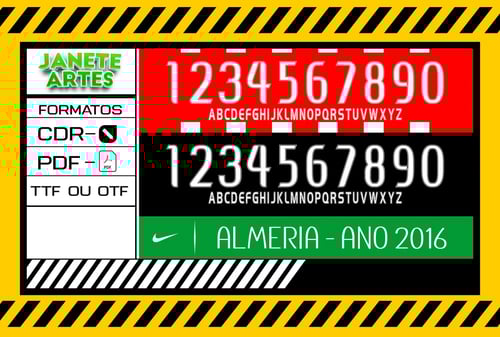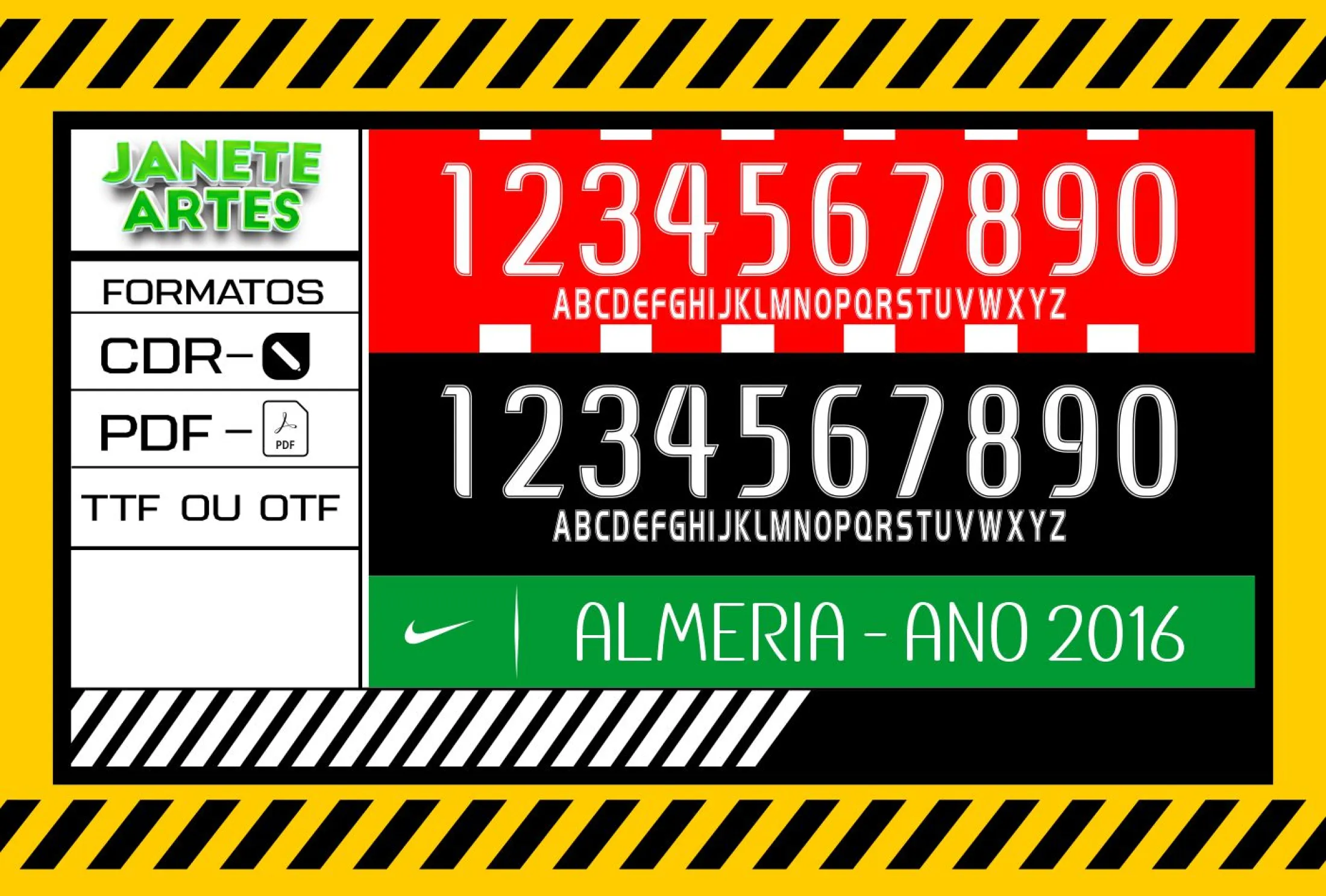
Fonte de Time Tipografia Almeria 2016
Download da Fonte de Time Tipografia Almeria 2016 para personalizar camisetas com design moderno e exclusivo. Arquivo digital perfeito para criar camisas de times, eventos ou presentes únicos e cheios de estilo.
Uma história de paixão e design
Imagine organizar a camisa perfeita para o seu time amador, aquele momento emocionante antes da partida em que todos vestem a mesma identidade. A Fonte de Time Tipografia Almeria 2016 nasceu exatamente dessa necessidade: unir estilo e personalidade em um design fácil de aplicar e que impressiona em campo e fora dele. Um jovem torcedor decidiu criar algo único para sua equipe, transformando a simples inscrição do nome do time em uma expressão visual forte, que inspira união e coragem.
O que você recebe com a Fonte de Time Tipografia Almeria 2016
• Fonte exclusiva pronta para ser aplicada em camisetas, camisas e blusas.
• Design de alta qualidade para personalização profissional.
Dicas para personalizar e combinar
• Combine a tipografia Almeria 2016 com cores vibrantes para criar destaque.
• Use tecido escuro para que a impressão clara da fonte ganhe mais evidência.
• Ideal para uniformes, grupos de corrida, times de futebol e eventos especiais.
Com a Arte Camiseta Fonte de Time Tipografia Almeria 2016 Personalizada, você terá uma obra de design exclusiva para destacar seu time ou grupo. Aproveite esta oportunidade para criar camisas que vão emocionar e unir todos em uma mesma paixão. A fonte tipográfica é moderna, marcante e fácil de aplicar.